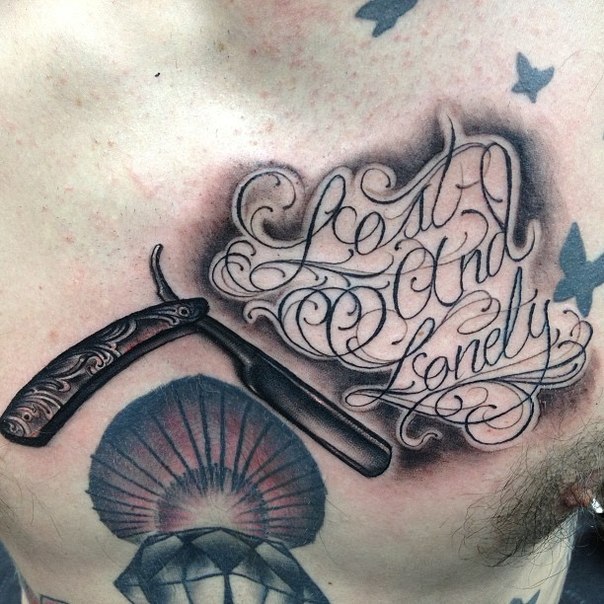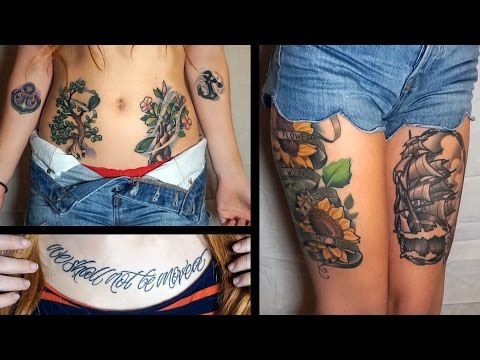
Шрифты для тату. Подбор шрифта для тату
Выбрали для татуировки цитату, имя любимого или собственное умозаключение? Стоит задуматься о шрифте для наколки. Эксперименты показывают, что восприятие текста во многом зависит от того, какими буквами он написан, с каким межстрочным интервалом. Возьмем, к примеру, интернет-шрифты. Один из них – Times New Roman. Им отпечатали несколько статей и журнала «Нью-Йорк Таймс».
Читателей попросили описать материалы. Публика сошлась на эпитетах «забавный» и «злой». Неудивительно, ведь статьи были едкого, сатирического плана. Однако, эти же публикации отпечатали шрифтом Arial и, на сей раз, почти никто не счел тексты забавными.
Так что, решите, какое впечатление должна производить новая наколка и выберите соответствующий шрифт для тату. Онлайн подобрать, как правило, предлагают лишь по эстетическим критериям. Мы же поможем совместить их с психологическим восприятием.
Шрифты для тату. Значение и психология
Все шрифты делятся на те, которые состоят из печатных букв и те, что имитируют рукописный стиль.
Возникают ассоциации не с бездумными машинами, выдающими шаблоны, а с личным письмом, в которое вложили душу. Поэтому и наколки, несущие эмоциональный посыл, лучше смотрятся в прописи.
В прописи больше округлостей. Плавные линии сопоставляются мозгом с чем-то дружественным и человечным. Поэтому, чтобы расположить к себе окружающих, восприниматься ими белым и пушистым, следует выбрать шрифт для тату близкий к письменному.
Печатные буквы взывают, главным образом, к разуму. Это упрощает подбор шрифта для тату философского характера. Но, не мешает учесть и аудиторию. К примеру, вы тенейджер. Наверняка, и надпись на теле адресована молодежи.
Она проще воспринимает шрифты бес засечек. Эти маленькие черточки на концах букв подсознание связывает с чем-то формальным. Формализм уместен лишь в догмах и отвергается юным поколением.![]()
Красивые шрифты для тату не обязательно должны быть крупными, или витиеватыми. На уровне подсознания небольшие буквы придают значимости тексту и его носителю. Создается впечатление, что это человек, который не нуждается в украшательствах, мысли которого мудры и весомы.
Отчасти, строки, размещаемые на теле, являются мыслями обладателя наколки. Текст выбирается тот, который совпадает с собственными убеждениями, соответствует значимым вещам в жизни человека.
Шрифты для тату. Дело в цвете
Подборка шрифта для тату требует учета не только формы, размера, наклона букв, расстояния между ними. Важен и цвет. Многие выбирают красочные наколки, не учитывая, как они будут смотреться при разных обстоятельствах.
К примеру, наступает вечер. Счастливый обладатель оранжевой надписи отправляется на прогулку. Но, желтые и оранжевые пигменты кажутся в сумерках менее яркими.
Буквы сольются в одно невзрачное пятно.
Тускнеет при плохом освещении и красный цвет. Его нередко выбирают для татуировок, несущих страстный посыл. Однако, в интимном полумраке страсть становится блеклой, а вот зеленая краска, напротив, смотрится более насыщенно. Это касается и синих, фиолетовых тонов.
Цветные пигменты в татуировках быстрее вымываются, разрушаются ультрафиолетом. Между тем, большинству требуются читабельные и четкие тексты. Так что, выбирая красочный эскиз, стоит быть готовым к его обновлению раз в 3-5 лет.
Мужские шрифты для тату
С помощью шрифта можно подчеркнуть энергетику и сексуальность представителя того, или иного пола. Мужскими считаются шрифты для тату-надписей, обладающие машинной стилистикой. Прямые, четкие, жирные линии ассоциируются с силой, стабильность, мощью. Это качества сильного пола, которые редко желают подчеркнуть женщины.
Динамику и агрессию, свойственные парням, отражают заостренные буквы. Это может быть стилизация, либо реальные исторические шрифты.
Для тату онлайн, к примеру, могут предложить славянскую рунную письменность.
Ей чужды округлые формы, к тому же, веды несут глубокий философский смысл. Размышления, передаваемые в татуировках, привлекают мужчин больше эмоциональных посылов.
Мужчинам не свойственно усложнять ситуацию. Выбирая в качестве наколки надпись, джентльмены, как правило, хотят, чтобы окружающие могли прочитать и понять ее. Именно этим психологи объясняют отказ парней от витиеватых шрифтов.
Они, действительно, влияют на восприятие. Так, группа студентов, которой выдали задачи, отпечатанные Arial, сочла ребусы легкими, быстро решила их. Второй группе те же задачи отпечатали Brush. Студенты нашли задания сложными, видимо, потому что приходилось вчитываться, отчего ускользала основная мысль.
Женские шрифты для тату
Подобрать шрифт для тату девушки стараются из категории рукописных. Женщин привлекают округлые буквы, завитки, хвостики.
Все это ассоциируется с плавностью, элегантностью, изысканностью и чувственность.
Большинство девушек не делают акцента на читабельности текста. Напротив, представительницам слабого пола нравится, когда в их послание приходится всматриваться, пристально изучать его. Это делает татуировку чем-то интимным, личным.